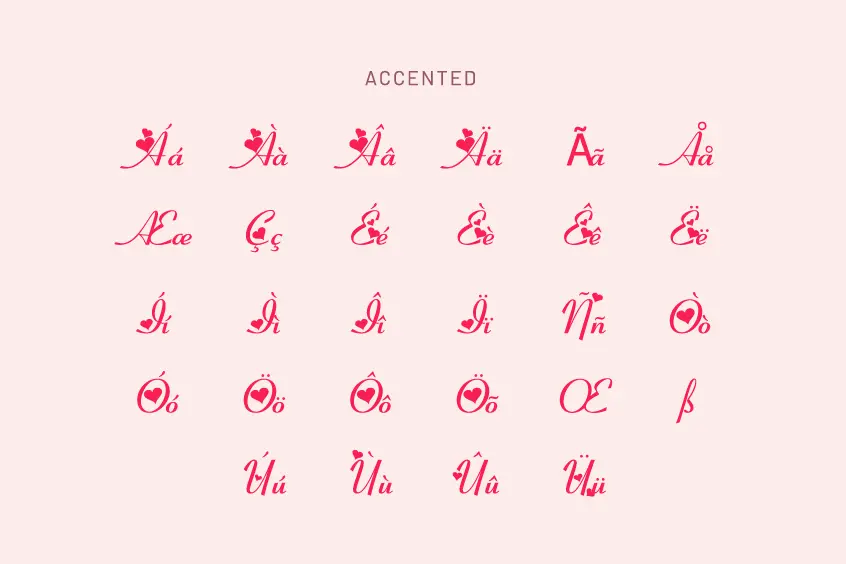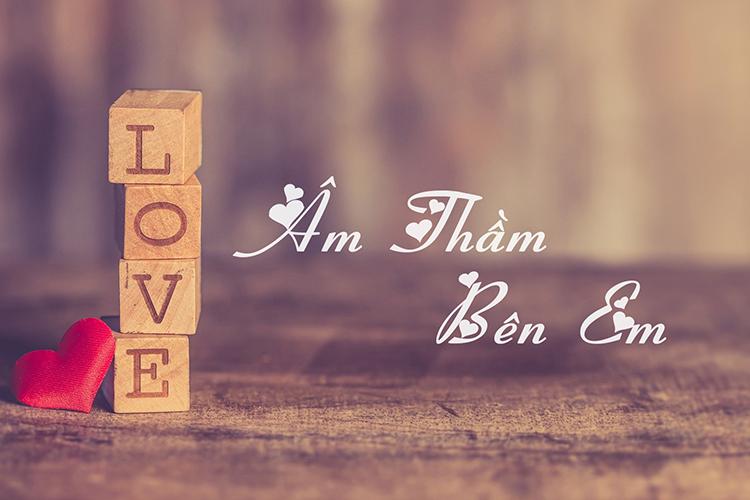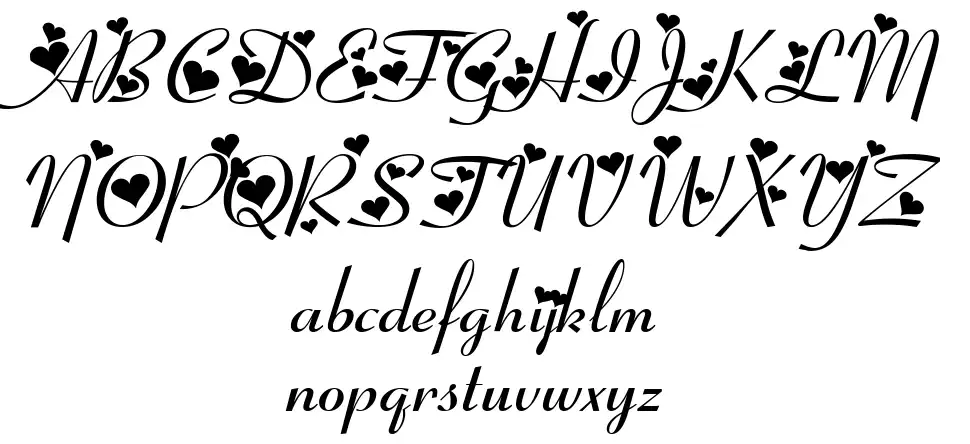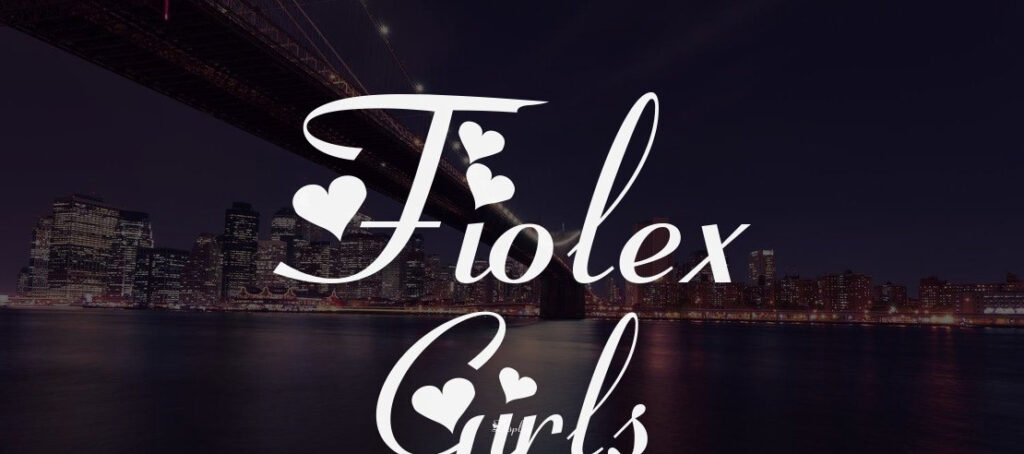
Font UVF Fiolex Girl là một bộ phông chữ thuộc dòng Script trang trí mang phong cách dễ thương, nổi bật với các chi tiết hình trái tim cách điệu lồng ghép tinh tế trên từng ký tự. Với vẻ ngoài mềm mại và tươi vui, phông chữ này thường được các kiến trúc sư, nhà thiết kế lựa chọn để tạo điểm nhấn cho các dự án homestay gia đình, phòng ngủ trẻ em hay các biển hiệu quán cafe phong cách lãng mạn.
Đặc điểm thẩm mỹ nổi bật của font UVF Fiolex Girl trong thiết kế
Nét cuốn hút đặc trưng của font Fiolex Girl Việt hóa nằm ở sự kết hợp giữa nét chữ viết tay tròn trịa và các họa tiết trái tim thay thế cho các dấu chấm trên chữ ‘i’, ‘j’ hoặc điểm xuyết ở các nét uốn lượn. Thiết kế này mang lại cảm giác ấm áp, gần gũi và giàu năng lượng tích cực cho thị giác người xem. Phiên bản tải font Việt hóa UVF Fiolex Girl đã được căn chỉnh hệ thống dấu thanh tiếng Việt cẩn thận, giúp các dấu hỏi, ngã, sắc, huyền nằm ở vị trí cân đối mà không làm che khuất các chi tiết trái tim đặc thù của bộ gốc.
Sự ổn định của bộ phông này còn thể hiện ở tính định hình phong cách rõ rệt. Khác với các dòng phông chữ kỹ thuật khô cứng, Fiolex Girl mang đến sự vui tươi, xóa nhòa cảm giác đơn điệu của các bức tường phẳng hay khối nhà kim loại. Đây là giải pháp phù hợp để ứng dụng vào các công trình nhà lắp ghép nghỉ dưỡng, góc sinh hoạt cho mẹ và bé hoặc những thương hiệu muốn truyền tải thông điệp về tình yêu thương, sự chăm sóc và vẻ đẹp dịu dàng.
| Phân loại phong cách | Decorative Script / Cute / Heart Accented |
| Mục đích phù hợp | Biển tên homestay, decor phòng ngủ, thiệp, quà tặng |
Tư vấn từ chuyên viên: Fiolex Girl là dòng phông chữ mang tính trang trí cao. Để bản vẽ hoặc ấn phẩm đạt hiệu quả thẩm mỹ tốt, bạn nên dùng phông này cho các tiêu đề ngắn hoặc tên riêng. Phần nội dung mô tả chi tiết nên kết hợp cùng một phông không chân đơn giản để người đọc dễ tiếp nhận thông tin mà không bị rối mắt.
03 Ứng dụng phông chữ Fiolex Girl vào thực tế công trình
Nhờ diện mạo ngọt ngào và giàu tính cảm xúc, bộ phông chữ này mang lại giá trị thực tế cao trong khâu trang trí và quảng bá các công trình hiện đại:
- Biển tên phòng cho Homestay gia đình: Những nét chữ uốn lượn kèm hình trái tim của Fiolex Girl rất ăn ý khi gia công trên chất liệu gỗ sáng màu hoặc mica pastel. Phông chữ này giúp các căn homestay lắp ghép toát lên sự mến khách và tạo cảm giác thư giãn cho các cặp đôi hoặc gia đình có con nhỏ.
- Trang trí không gian phòng ngủ trẻ em: Bạn có thể dùng font này để cắt decal dán tường, làm bảng tên góc học tập trong các căn hộ nhà lắp ghép, tạo nên một không gian tuổi thơ sinh động, khơi gợi trí tưởng tượng và sự vui vẻ cho trẻ.
- Thiết kế góc check-in và ấn phẩm sự kiện: Độ nhận diện dễ thương của phông chữ hỗ trợ đắc lực cho việc làm các biển bảng trang trí photobooth, menu tiệc trà nhỏ tại sảnh đón khách văn phòng container, tạo thiện cảm với người ghé thăm.
03 Lưu ý kỹ thuật để bố cục font chữ Fiolex Girl tinh tế và dễ nhìn
Để khai thác hiệu quả vẻ đẹp của dòng font đặc thù này mà không gây cảm giác sến súa hay khó đọc, người thiết kế nên lưu tâm một số kinh nghiệm sau:
- Tránh viết hoa toàn bộ cụm từ: Các ký tự hoa của Fiolex Girl có nhiều đường uốn lượn và họa tiết trái tim lớn. Việc viết hoa toàn bộ từ sẽ làm các chi tiết dính vào nhau, gây rối mắt và làm giảm đáng kể khả năng đọc hiểu.
- Kiểm soát khoảng cách dòng: Do một số nét chữ có chi tiết trái tim vươn lên cao hoặc hạ thấp, bạn nên nới rộng khoảng cách giữa các dòng để văn bản giữ được sự thông thoáng và tinh tế.
- Lựa chọn màu sắc dịu nhẹ: Phông chữ này phát huy hiệu quả thị giác cao khi phối cùng các tông màu pastel như hồng phấn, kem sữa, xanh bạc hà hoặc trắng trên nền gỗ tự nhiên, giúp tôn lên nét ngây thơ và tươi mới của bộ chữ.